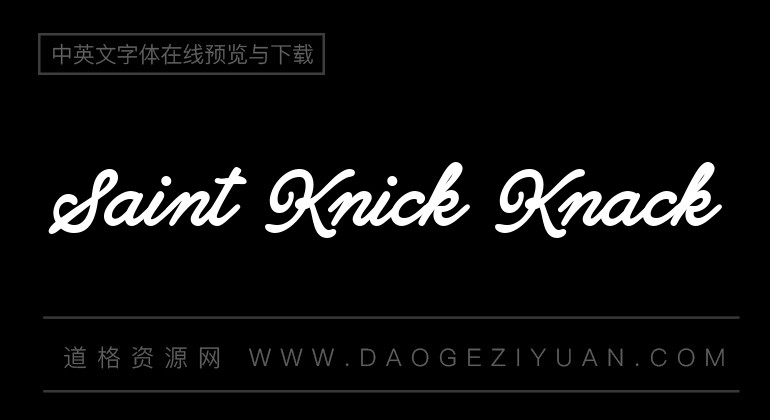
Saint Knick Knack
? Saint Knick Knack 是一款具有复古风格的字体,它的特点是细节处理精细,给人一种古典沉稳的感觉。这款字体的字形比较细腻,有着柔和的曲线和流畅的线条,具有细致华丽的特点,适用于各种报刊杂志,书籍,海报等印刷品。
Saint Knick Knack是一款非常不错的手写艺术字体,具有很好的视觉感,适合于文化类的宣传设计、商业类品牌的广告和产品包装设计以及个性化文字排版等较多场景。